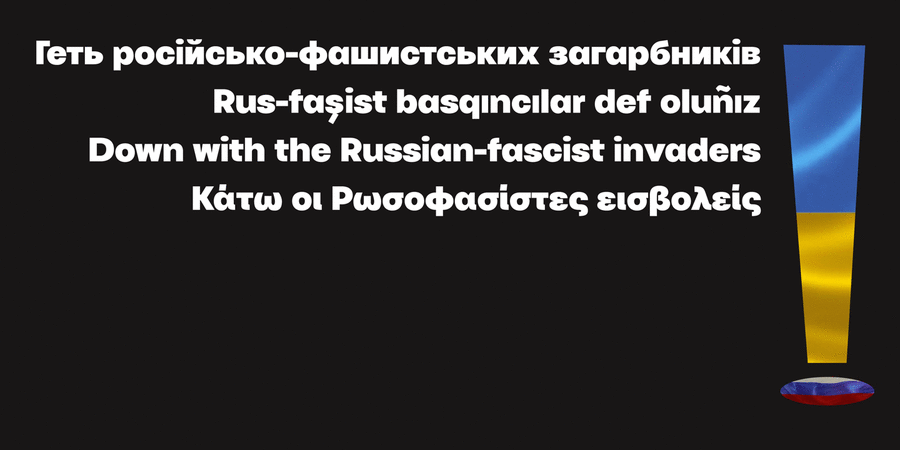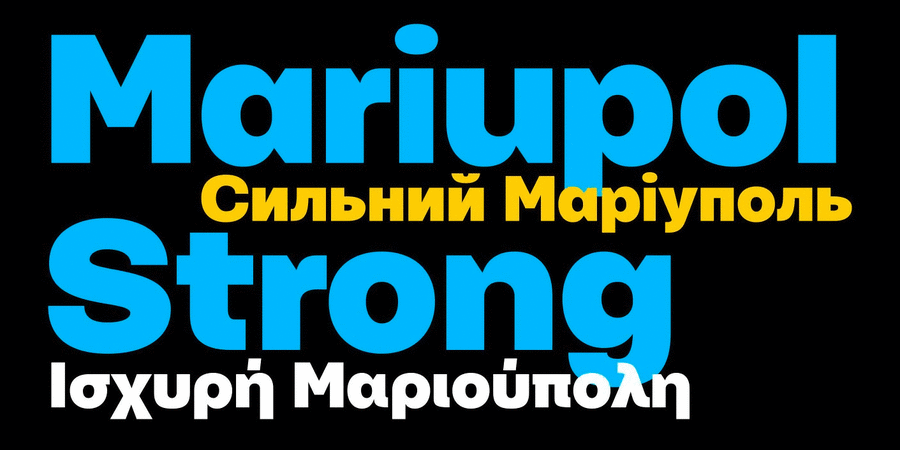
Опис шрифта Mariupol StrongНаджирне накреслення виразного гротеску, придатне як для бойових постерів, так і для вишуканого сучасного дизайну. У складі — базова латинка, слов’янська кирилка, монотонічна гречка та купа смаколиків: найактуальніші ліґатури, початкові та кінцеві розчерки, альтернативні літери тощо. Шрифт розробила анонімна творча группа у 2022 році.
Асоціації з сімейством шрифтів Mariupol StrongОсобистість і характер гарнітури:
міський, сучасний, формальний, рівний, якісний, різкий, чіткий, яскравий, важкий, сильний, серйозний, впевнений, стійкий, переконливий, твердий, потужний, мотивуючий, помітний, важливий, тісний, суворий, техногенний, амбітний, значний, міцний, мужній, кондовий, добротний, щільний, монументальний, технічний, гучний, надійний, індустріальний, урбаністичний, авторитетний, діловий, крутий, залізничний, солідний, самостійний, енергійний, характерний, залізний, сталевий, статичний, здоровий, робочий, відповідальний, західний, точний, прямокутний, стабільний, логічний, прагматичний, практичний, машинний, інженерний, обов'язковий, архітектурний
Місто, дизайн, взуття, техніка, інструмент, будівництво, машинобудування, завод, промисловість, верстат, тренажери, енергетика, паливо, електростанція, сейф, екскаватор, металургія, вантажоперевезення, порт, вантажівка, далекобійник, двигун, урбаністика, прес, вагон, залізниця, бізнес, торгівля, магазин, реклама, Футбол, кіно, код, тара, зброя, креслення, конструктор, інженер, автоматика, мотор, ГОСТ, шолом, уніформа, страйкбол, архітектура, електроніка, аптека, ліки, транспорт, сталевар, архітектор, робочий, рентген, банкнота, монета, логістика Гарнітура асоціюється з віком: